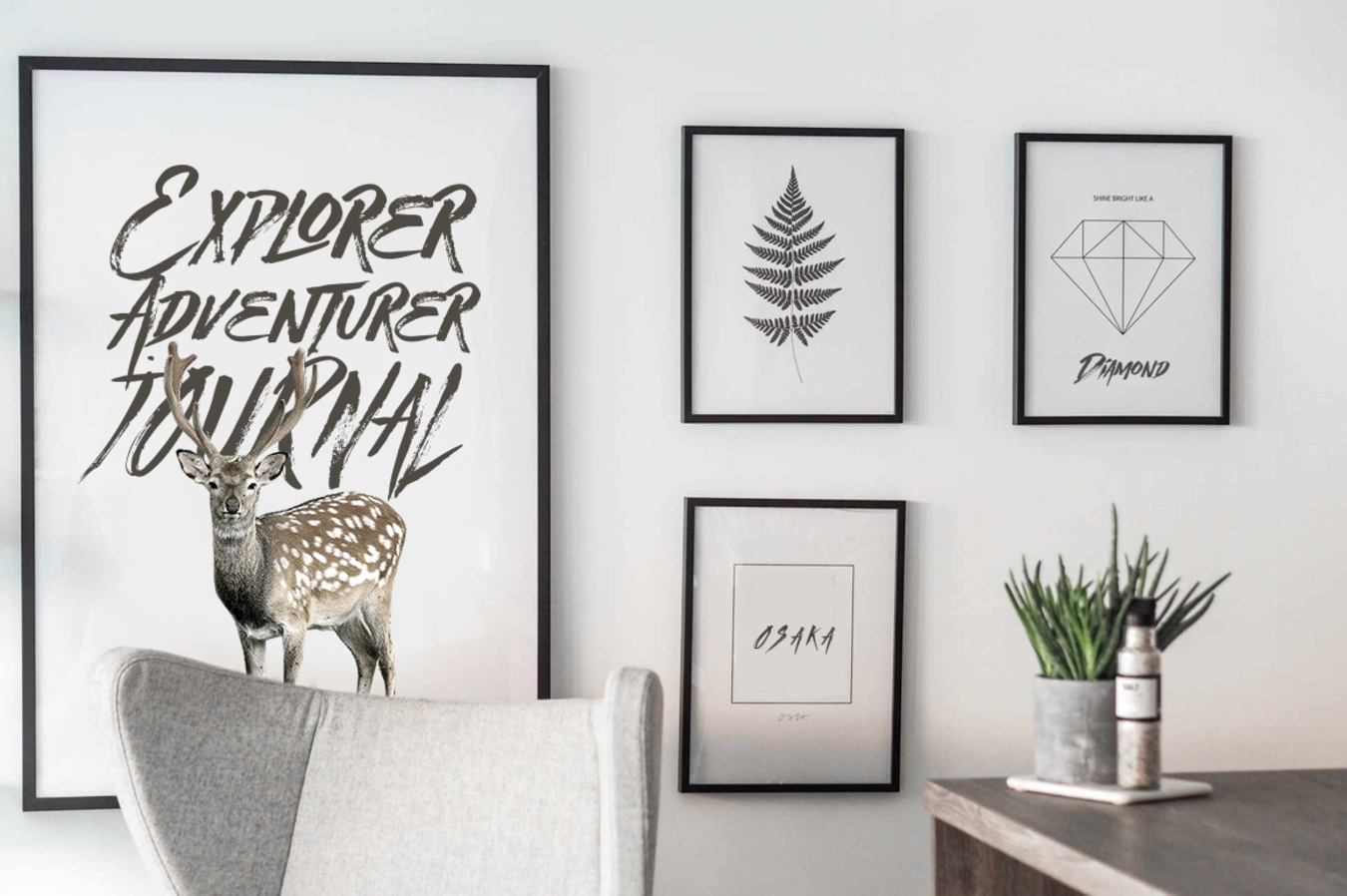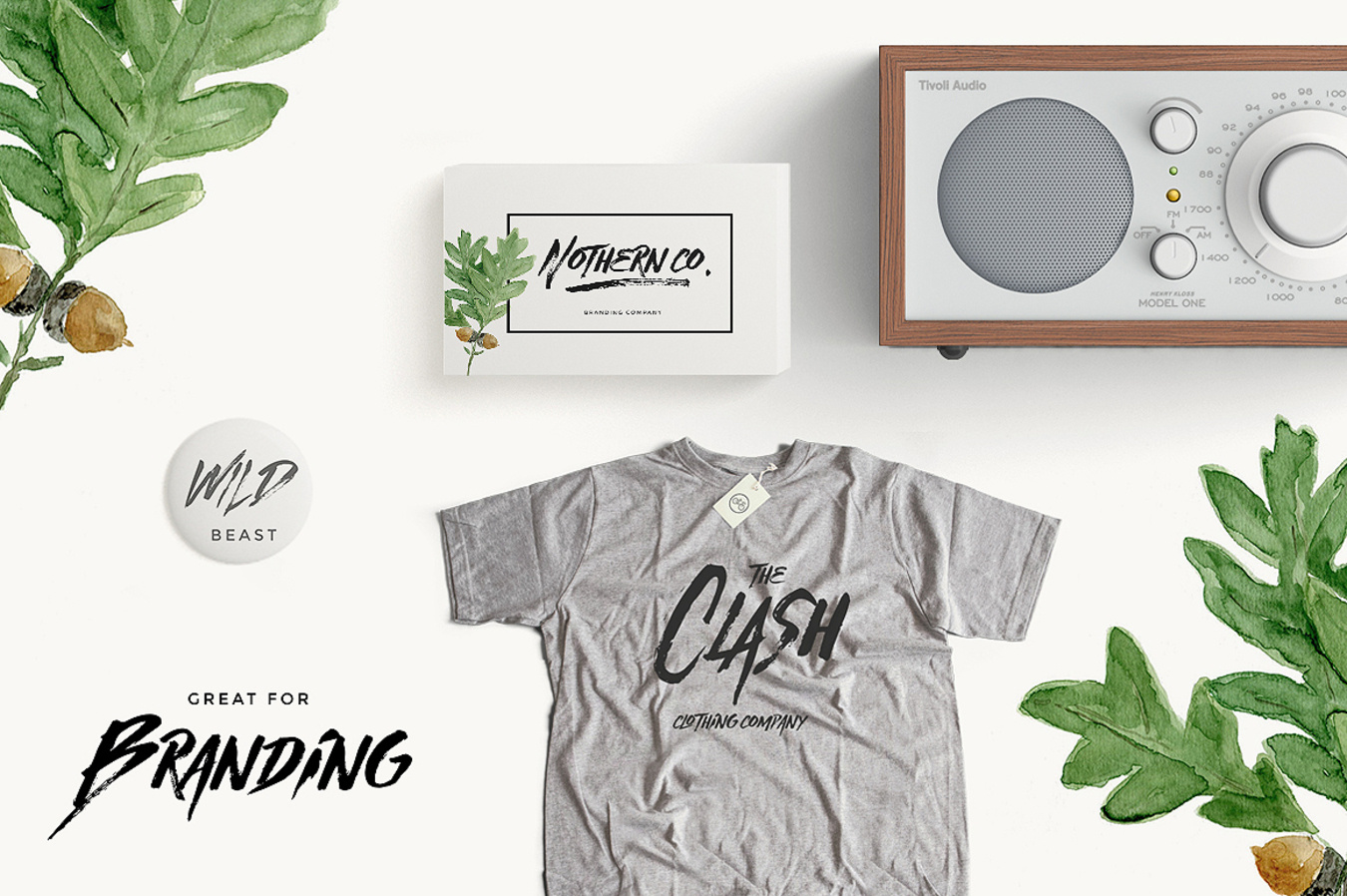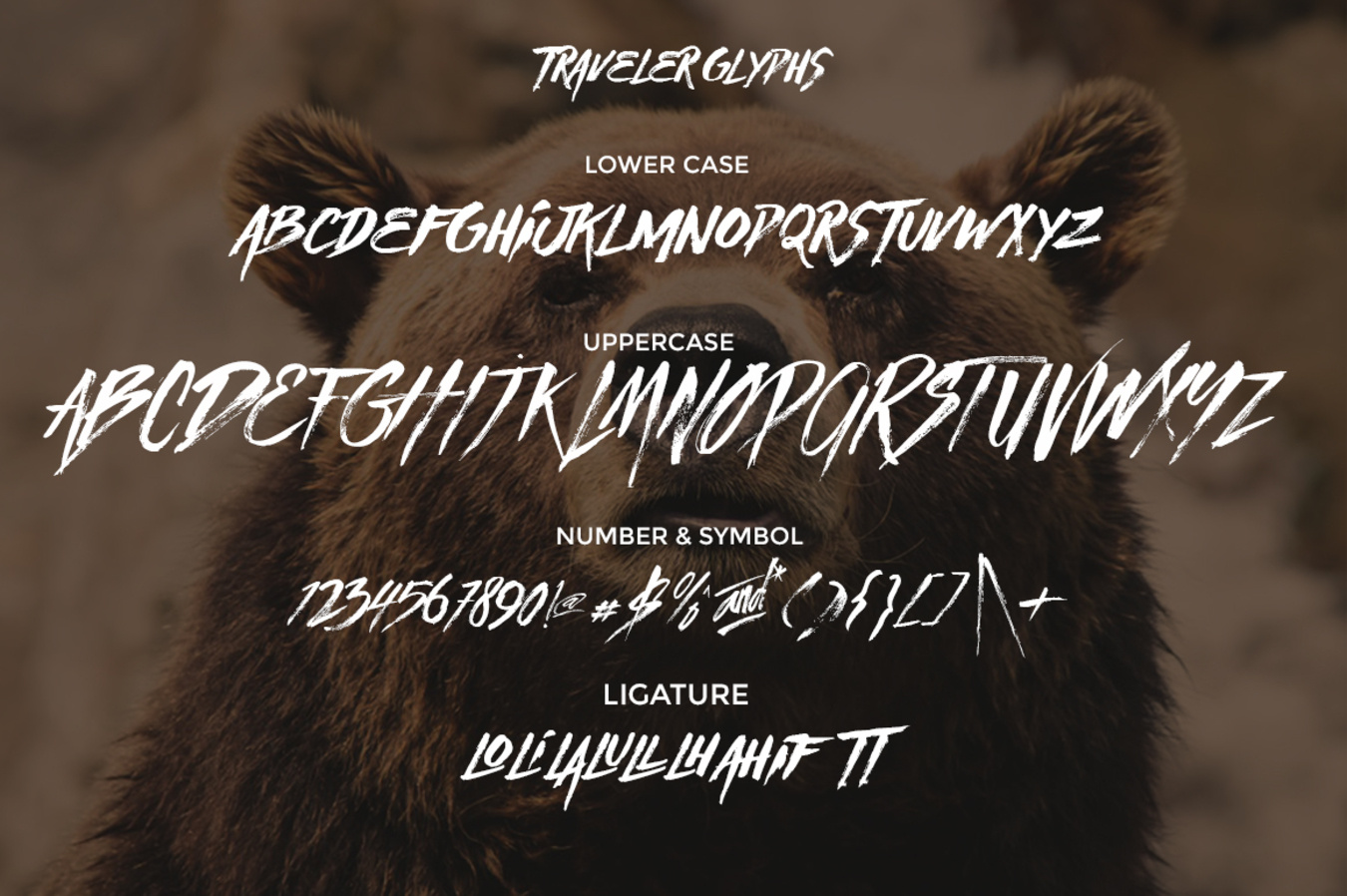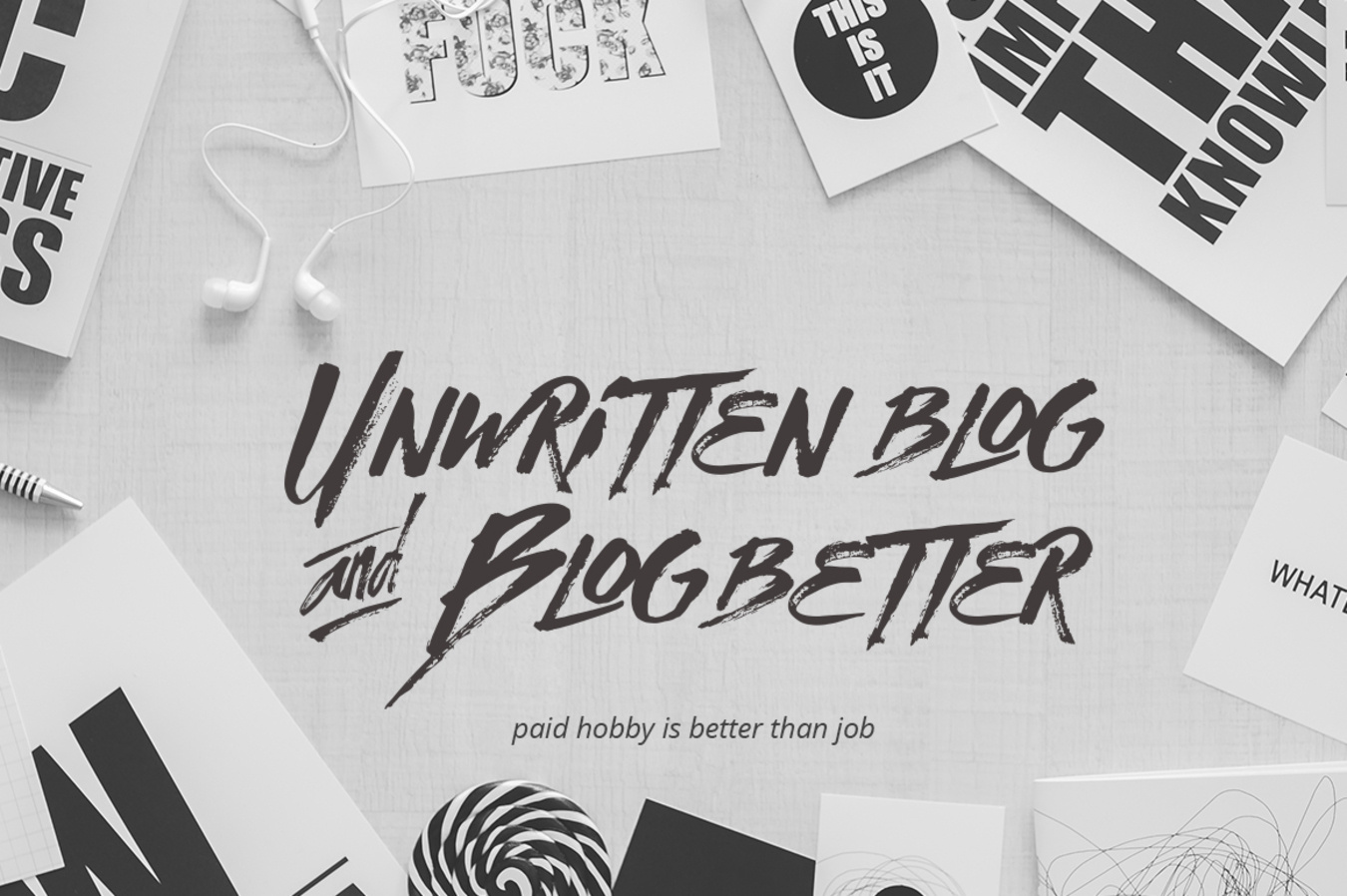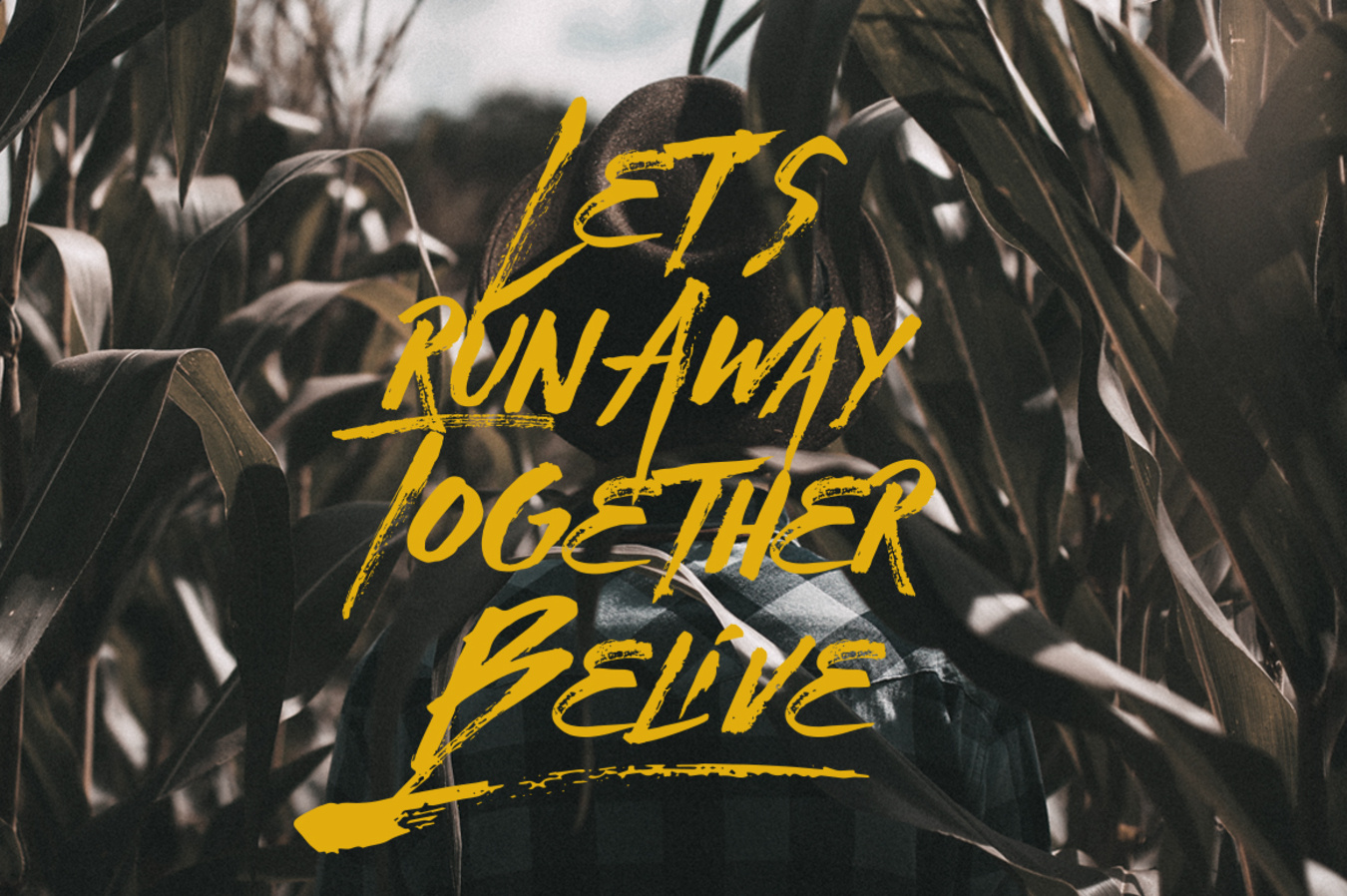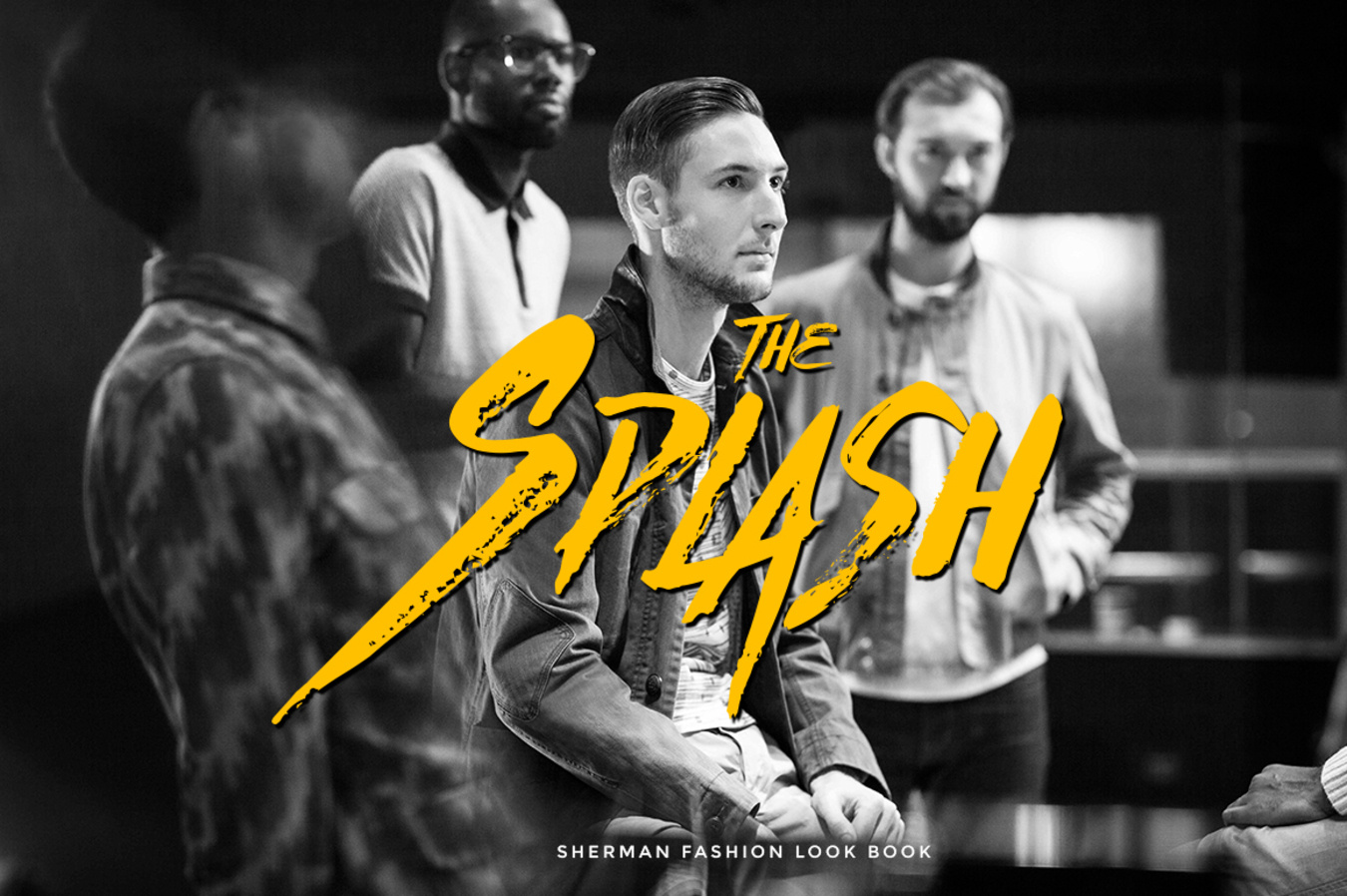
独特制作的手工刷风格化字体,Traveler Brush Type
A uniquely crafted handmade brush stylized typeface, Traveler Brush Type
旅行者精心制作,带有漂亮的刷式手绘外观,精巧的基线冒险概念,大胆的角色和酷炫的结合。完美的徽标标记,印刷报价,包装,博客标题等等。 通过包含令人敬畏的连线,您可以制作独特的角色,完美适合您的主题。